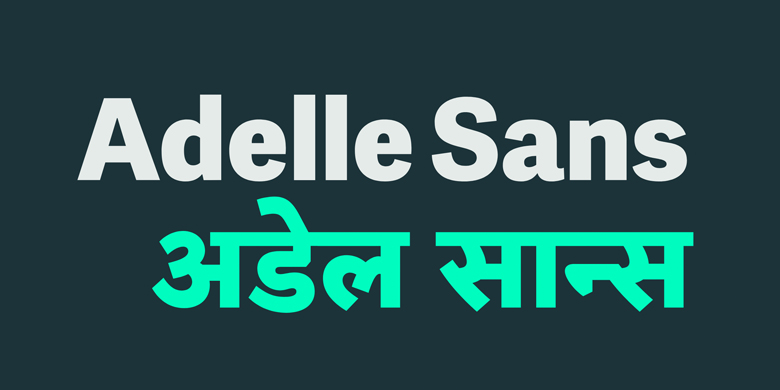
Adelle Sans DEV
字体品牌: TypeTogether 设计师:José Scaglione,PoojaSaxena,ErinMcLaughlin,VaibhavSingh 字体分类:无衬线体 字体属性:外文 字符集:Unicode 发布时间: 2018
一款低笔画粗细对比的天城文家族,在所有的文本环境中都能灵活且风度翩翩。原有的Adelle Sans,是José Scaglione和Veronika Burian的获奖无衬线字体,提供了一个更清晰且精神饱满的无衬线体,取代了传统的奇形怪状的无衬线体。在2013年,Veronika和José在英国雷丁大学的集中课程中开始了天城文项目。几年后,Erin McLaughlin和Vaibhav Singh继续进行研究和设计。当Pooja Saxena于2017年加入TypeTogether时,Adelle Sans 天城文家族开始独立。总之,Adelle Sans天城文将拉丁文转换成超过4亿人使用的语言,超过全印度的三分之一的人口使用的语言。与TypeTogether的字体一样,在创建Adelle Sans天城文时考虑了最苛刻的编辑设计问题。